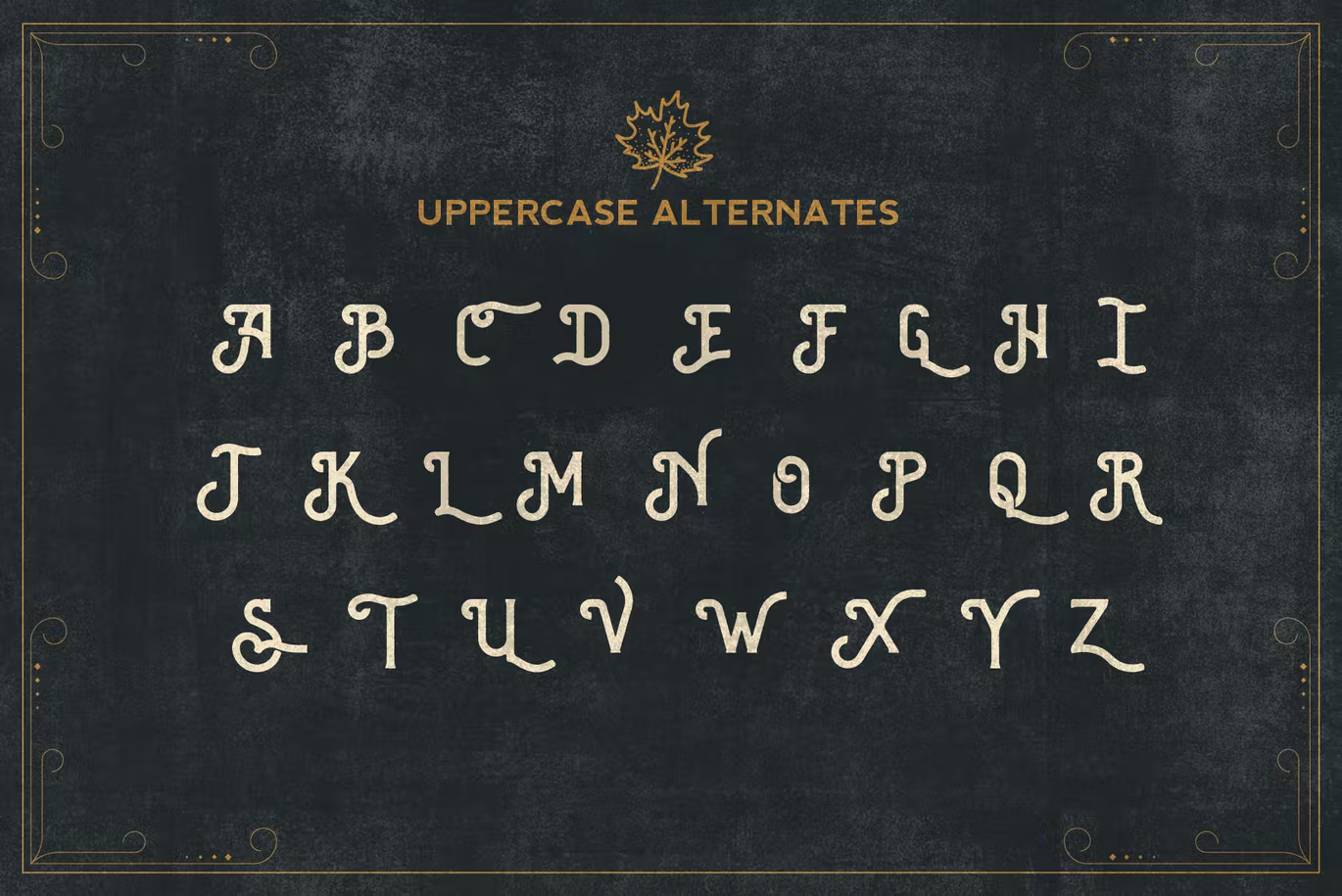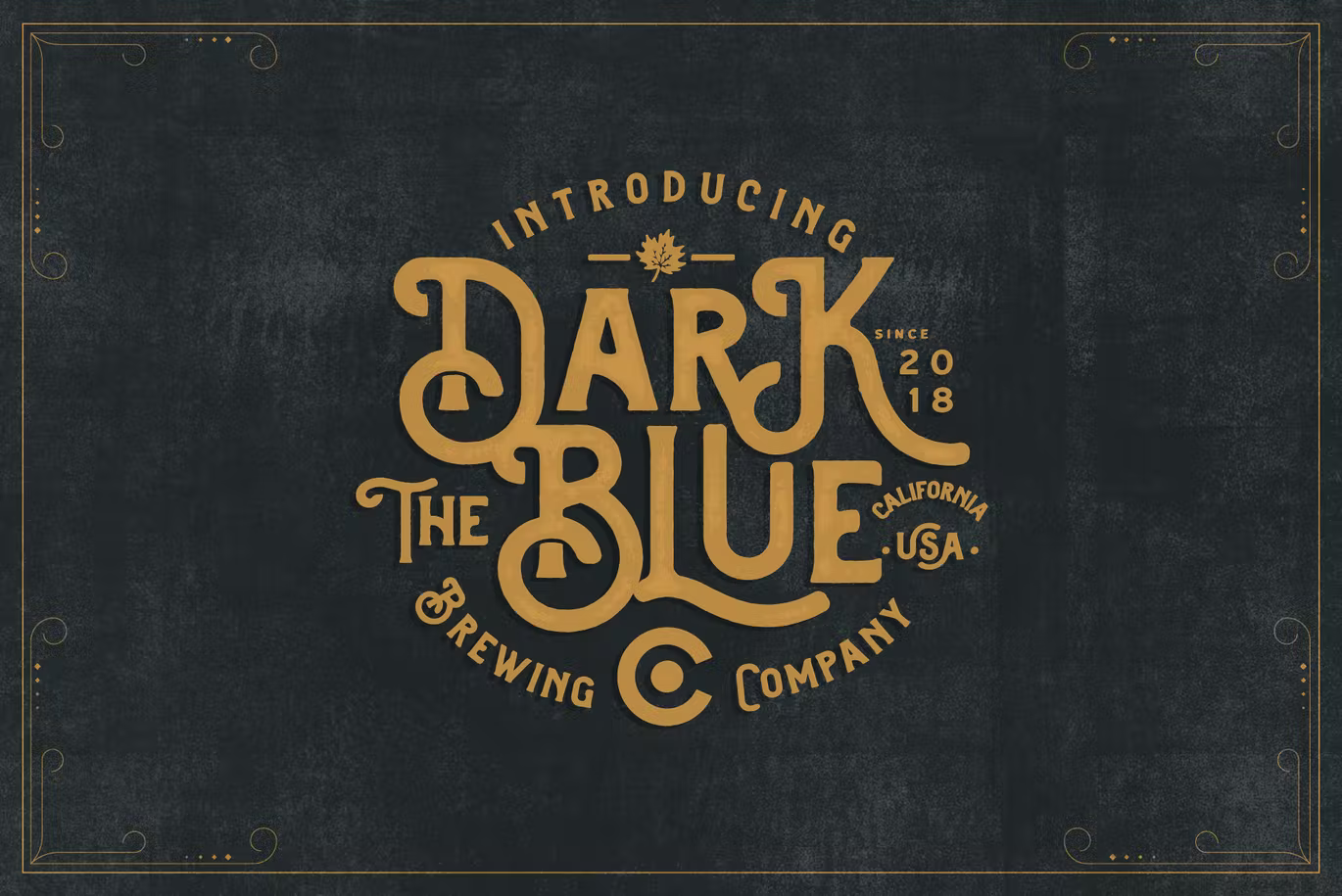
Brewski Font
Description de Brewski Font
Brewski Font est une police à empattement d’affichage avec un style vintage dessiné à la main, et une touche d’ornement donne à cette police un aspect élégant. Inspiré des emballages de brasserie vintage et de la publicité pour la bière du début du 20e siècle. Il est parfait pour la conception de logos vintage, de titres ou de packaging. Brewski a été conçu avec des alternatives stylistiques et contextuelles dans certains caractères qui vous permettent de mélanger et d’associer des paires de lettres pour les adapter à votre conception. Cette police convient au design vintage, aux t-shirts, aux logos, aux étiquettes, aux affiches, etc.
CARACTÉRISTIQUES
Jeu de caractères A-Z avec lettres majuscules spéciales
Alternatives stylistiques
Chiffres et ponctuation